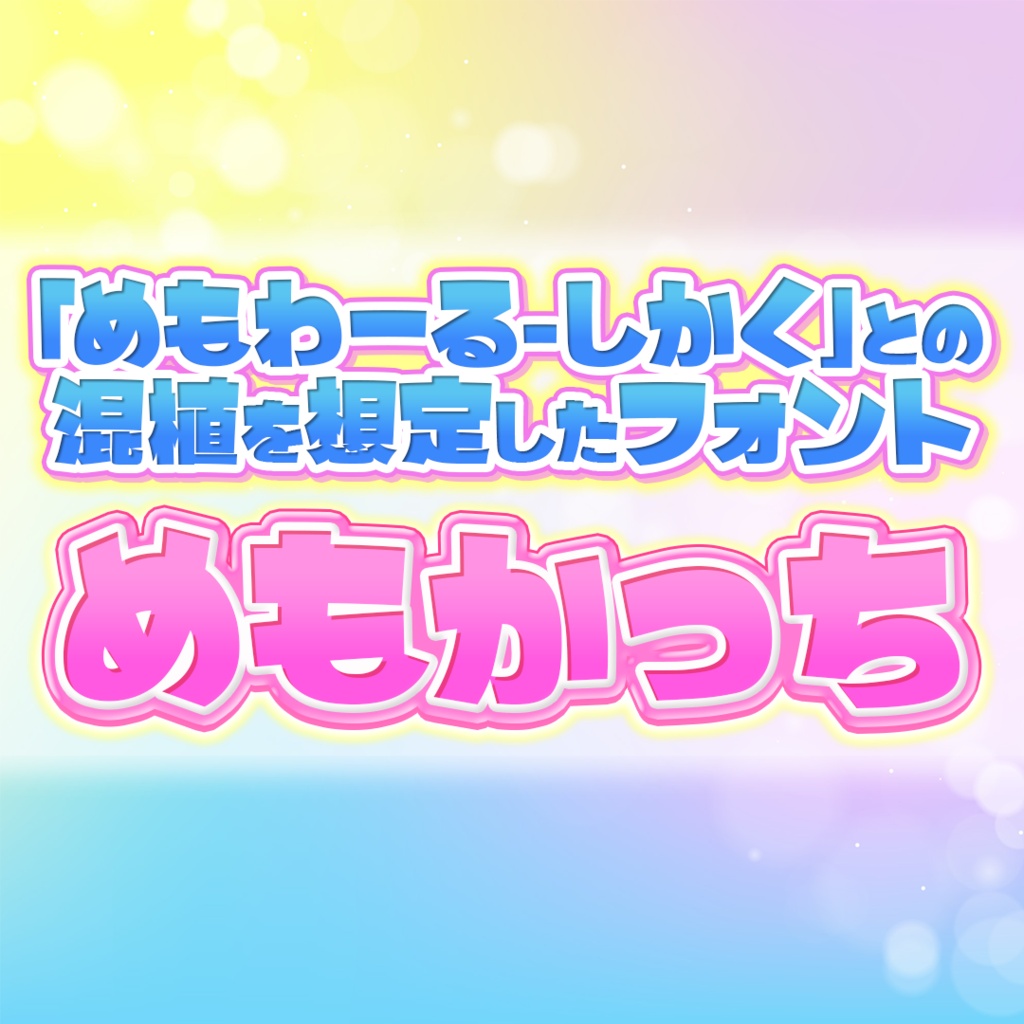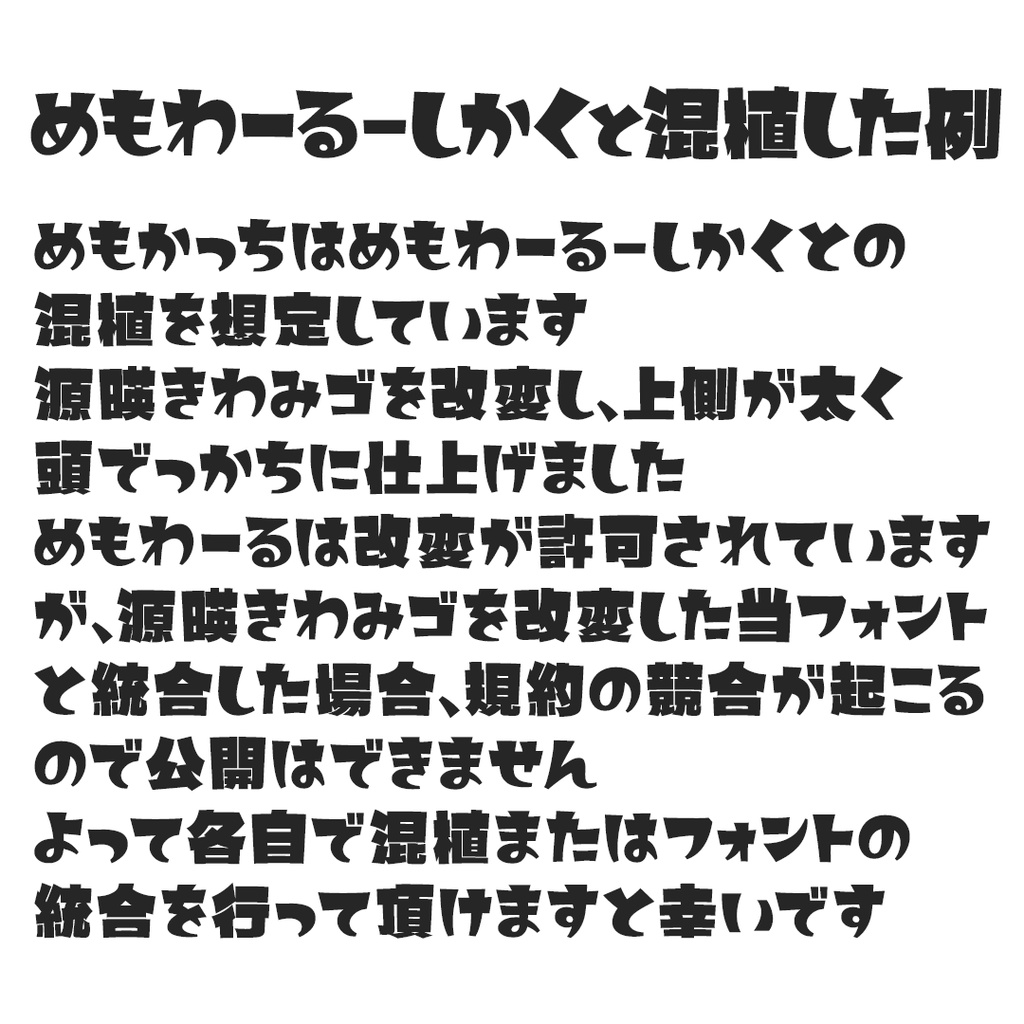
めもかっち【フリーフォント】
めもかっち 概要 当フォントは「源暎きわみゴ」を加工したフォントです。 「めもわーる‐しかく」と混植することを目的として作成しました。 そのため、サイズもめもわーるに合わせていますので、各自で混植もしくはフォントの統合をしていただけますと幸いです。 中身は同じですが、投げ銭版もございます。ご支援いただけましたら幸いです。 ライセンス 当フォントはSIL Open Font License1.1の下で公開いたします。 個人利用・商用利用にかかわらず無償で使用可能です。 SILライセンスにつきましては以下をご確認ください。 ライセンス原文 http://scripts.sil.org/OFL ライセンス原文日本語サイト https://licenses.opensource.jp/OFL-1.1/OFL-1.1.html ライセンスざっくり解説 https://tanukifont.com/sil/ 免責事項 当フォントの使用に関しては全て無保証とさせていただきます。 謝辞 全ての関係者の皆様に深くお礼申し上げます。 源暎きわみゴ https://okoneya.jp/font/genei-kiwamigo.html 詳細 お問い合わせ等ございましたらBOOTHの「ショップへのお問い合わせ」よりお願い致します。 めもかっち 制作:やっちゃん https://yattyann.booth.pm/ フォント公開・利用規約制定 2026年5月10日